精密さを表現する書体
D&DEPARTMENT PROJECT(ディアンドデパートメントプロジェクト)は、2000年にデザイナーのナガオカケンメイ氏によって創設された、「ロングライフデザイン」をテーマとするストアスタイルの活動体です。現在は、東京やソウルなど国内外に11店舗を展開する他、デザインコンサルティングを行うD&DESIGN、47都道府県の個性をまとめた観光ガイドを発行する d design travelなどへ活動を広げています。
「自分たちのこととして考えられないものはやめましょう、というスタンスで活動しています。創業当初に60VISION(ロクマルビジョン)を立ち上げて、老舗の日本メーカーの工業製品の若者向けリブランディングのコンサルティングをしていました。自社のプロジェクトに専念するために、それ以外の仕事はお断りをしていたのですが、『ロングライフデザイン』という考え方に賛同してくれるお客様が増えてきたのでデザインセクションを作り、お客様のご依頼にお応えすることにしました。店舗を持っているデザイナーの強みを活かした仕事ができていると思っています」と松添氏は語ります。
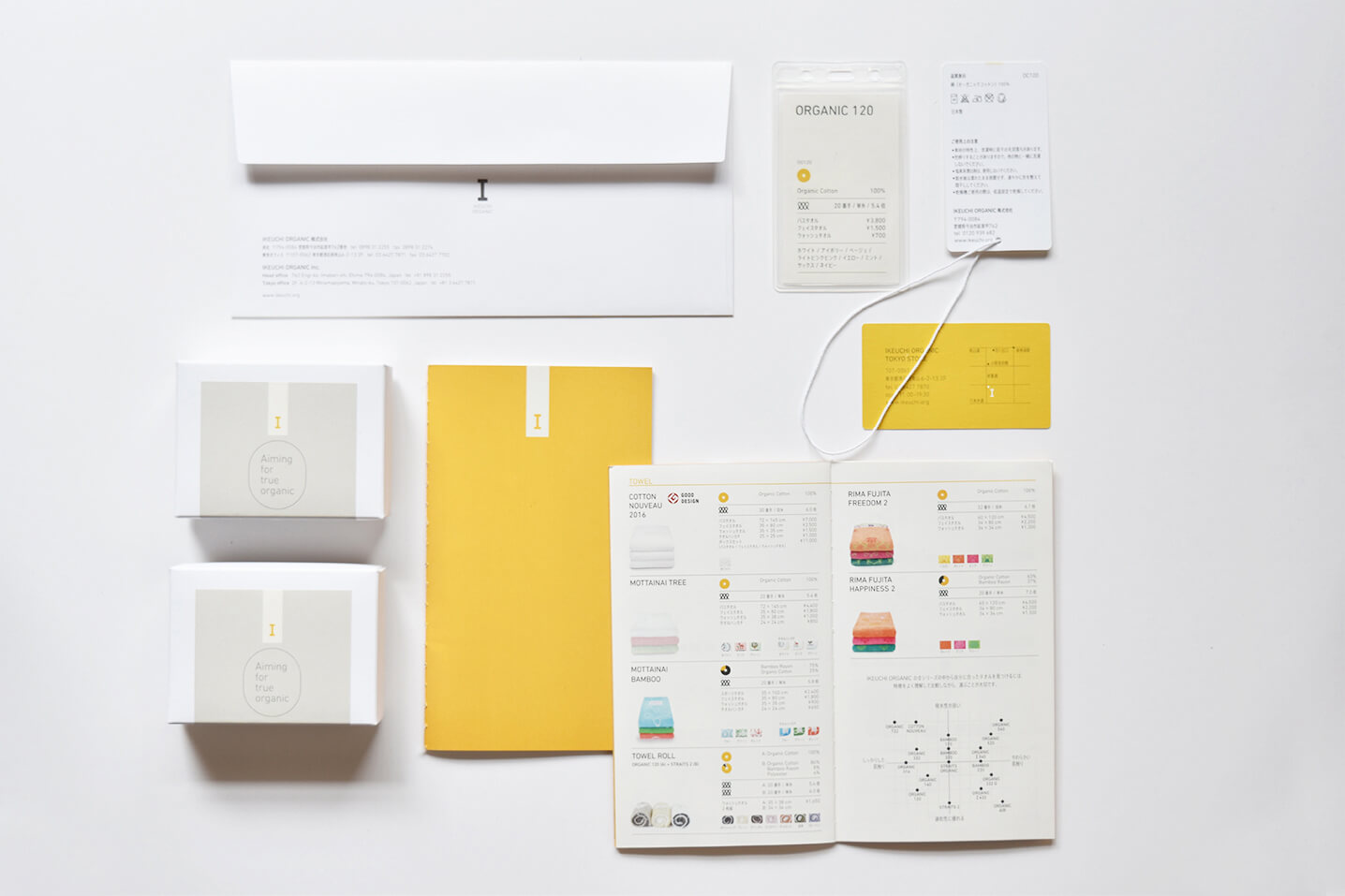
D&DEPARTMENTは、「オーガニックに精密さを」をコンセプトとする、今治タオルの池内オーガニック社のリブランディングを依頼されました。池内オーガニック社は、原材料の調達から最終製品に至るまでの安全性と環境性のデータを全て公開している企業です。そのカタログやパッケージ、ラベルなどすべてにAXIS Fontが採用されています。
中川氏はAXIS Fontコンデンスを選択した理由を、「カタログでは素材や構造を伝えるための情報量が多く、限られたスペースですべてを伝えることができる書体を選ぶことが重要でした。また、タオルを並べた時の精密さを表現することも書体に求めました」と語っています。
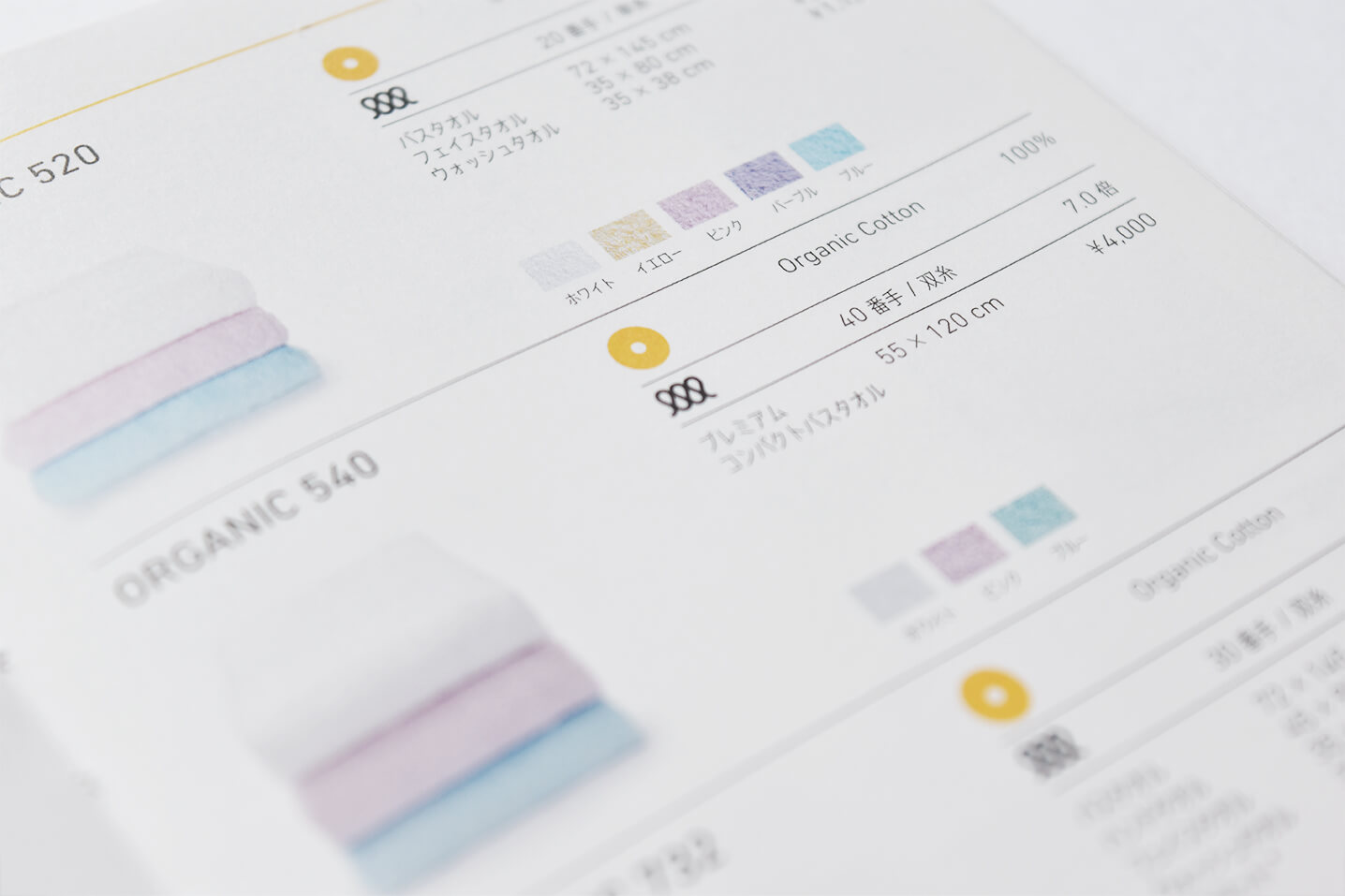
D&DEPARTMENTのプロジェクトは、ロングライフデザインという考え方が根底となっています。新規の依頼を受けた場合は、複数セクションへのインタビューでキーワードを抽出し、企業の個性やアイデンティティを示すブランドブックを策定して、パッケージやユニフォーム、名刺、インテリアなどに展開していきます。その企業が培ってきたものや変えるべき部分を一緒に判断することで、クライアント企業と長く継続した関係を築いています。
ロゴやカタログ、パッケージなどブランディングに関わる部分は、D&DEPARTMENTが制作し、お客様への手紙やプレスリリースなどはフォーマットを提供しています。クライアント企業には、日常業務で使用する必要最小限のフォントの購入を提案することで経費節減にも貢献しています。
D&DEPARTMENTは、2014年から渋谷ヒカリエが主催する物産展の企画を行っています。
2016年は、渋谷という個性を出しながら、マルシェでの販売と、その野菜を使ったレストラン、トークショーなど本来の農業を考えた「文化的体験」ができるアグリカルチャー物産展として展開しました。
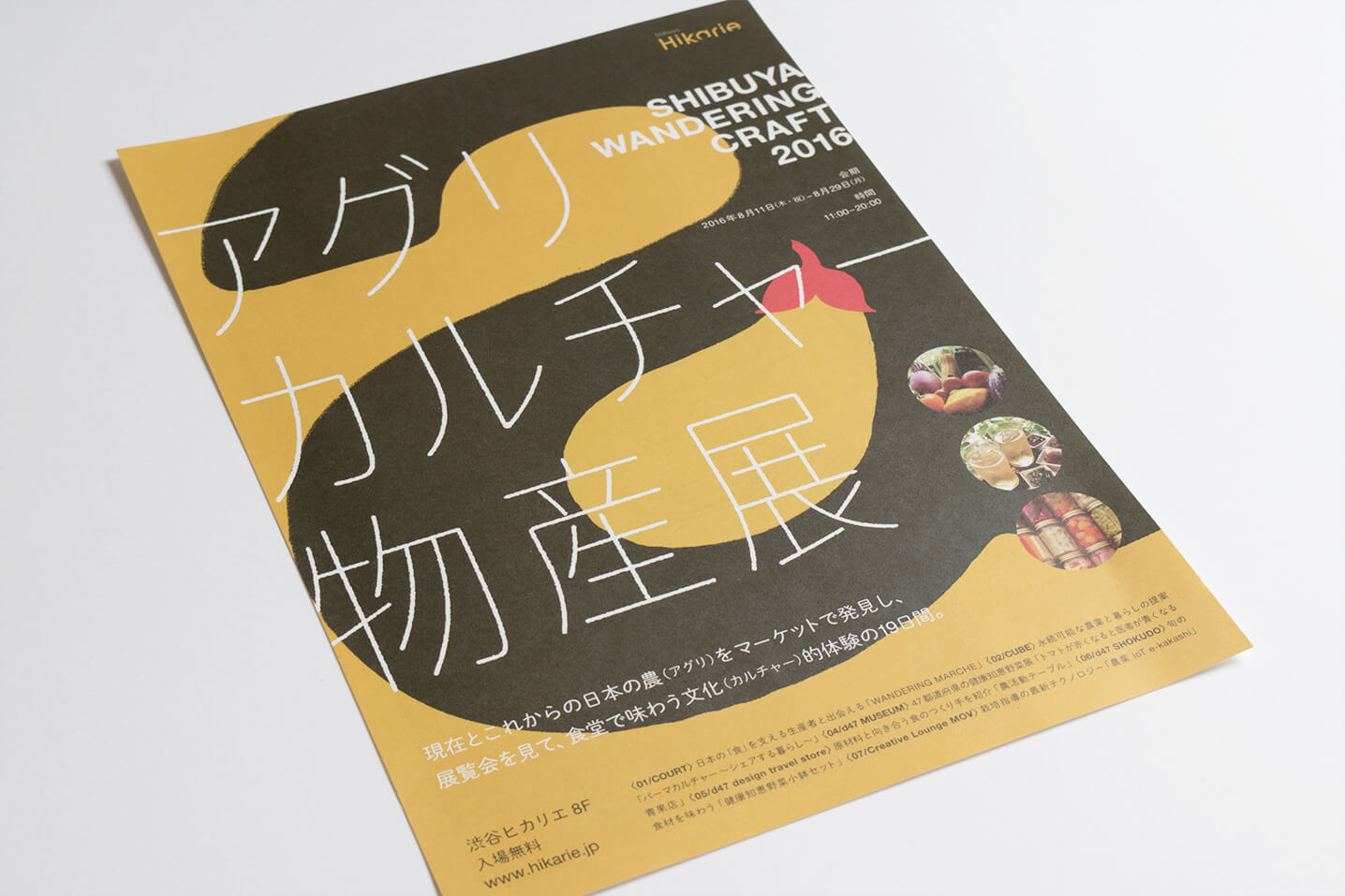
「メインビジュアルでは、『アグリカルチャー物産展』という文字を大きく使う必要がありました。一列に配置したときに横広がりになり過ぎず、3行にして字間を空けてもおさまりがいい。背景のグラフィックスの邪魔をすること無く、縦でも横でも綺麗に展開できるフォントはAXIS Fontコンデンスしかないと思いました。食品らしさを出すため、キャッチコピーでは角を落として使っています」と中川氏は語ります。
良い食品づくりの会が主催した博覧会でも、DINコンデンスとAXIS Fontコンデンスが選ばれました。
「このイベントでは商品の美味しさだけではない、生産者たちのものづくりにかける想いや、彼らの商品やその取り組みを通して正しい食のあり方を伝えていくことがミッションでした。食のイメージを優先するなら、シズル感と表現されるような食っぽいフォントが好まれる傾向にありますが、ここでは、アカデミックでありながら、かつ食のイメージも邪魔しないフォントとして選びました。」(松添氏)